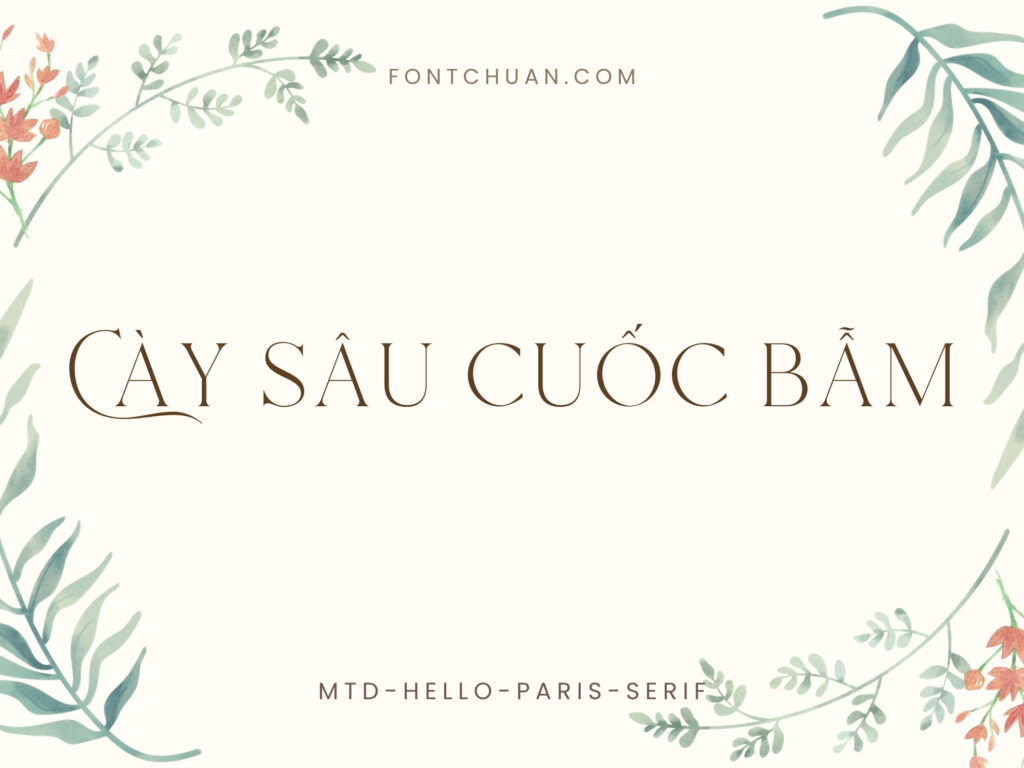
Font MTD Hello Paris Việt Hóa
Tác giả Font: Sans & Sons
Font MTD Hello Paris Serif là một kiểu chữ serif hiện đại, kết hợp giữa phong cách cổ điển và đương đại, mang đến vẻ đẹp sang trọng và tinh tế. Được thiết kế bởi Sans & Sons và Việt hóa bởi Mộc Hạ, font này hỗ trợ đầy đủ tiếng Việt cùng hơn 90 ngôn ngữ khác, mở rộng khả năng ứng dụng trong các thiết kế đa ngôn ngữ. Đây là một trong những phông chữ được cộng đồng thiết kế đánh giá cao và sử dụng trong nhiều dự án sáng tạo, đáp ứng nhu cầu đa dạng của người dùng.
MTD Hello Paris Serif nổi bật với các đường nét thanh lịch và tinh tế, mang đến cảm giác chuyên nghiệp và đẳng cấp. Font rất phù hợp cho các thiết kế logo, tiêu đề, bao bì sản phẩm, thiệp mời và các ấn phẩm đòi hỏi sự sang trọng và nghệ thuật. Các ngành nghề phù hợp bao gồm quảng cáo, giáo dục, công nghệ, thiệp cưới và ảnh cưới. Font này cũng lý tưởng cho các sự kiện như Tết, Giáng sinh, Valentine và các lễ hội khác.